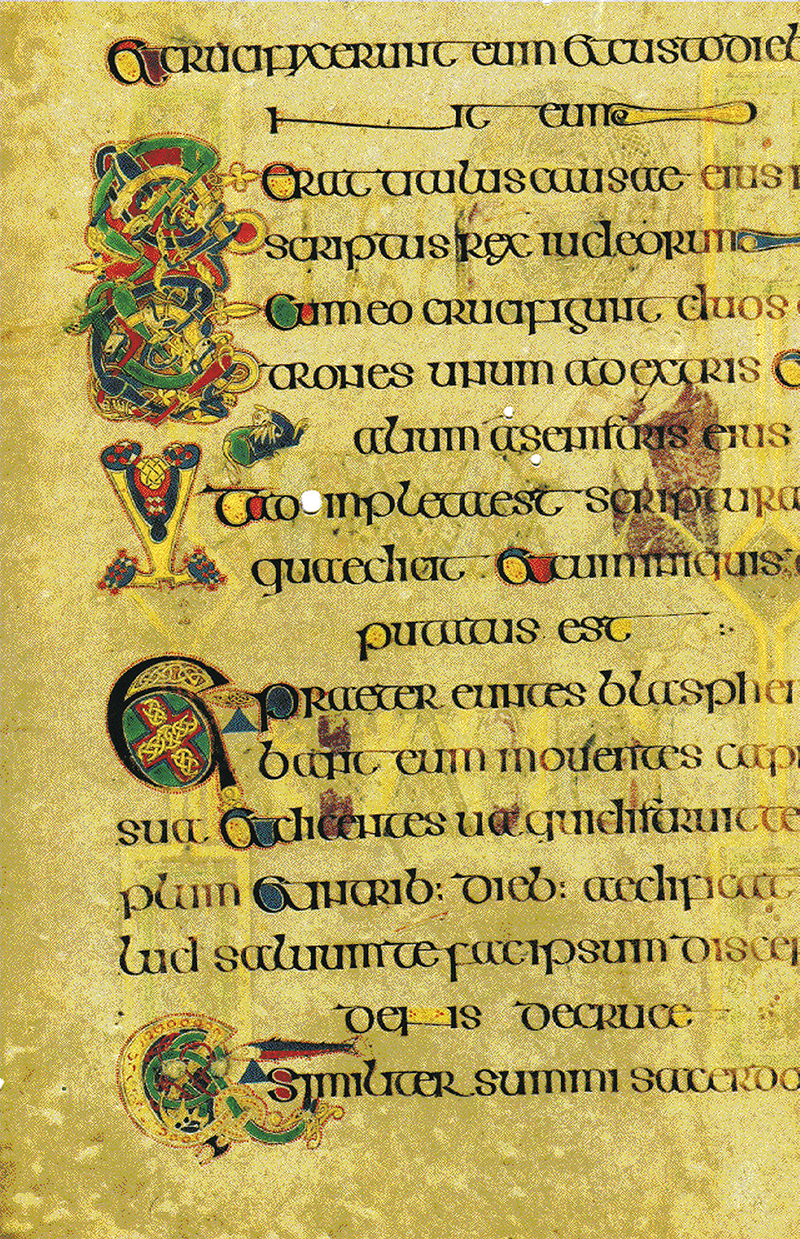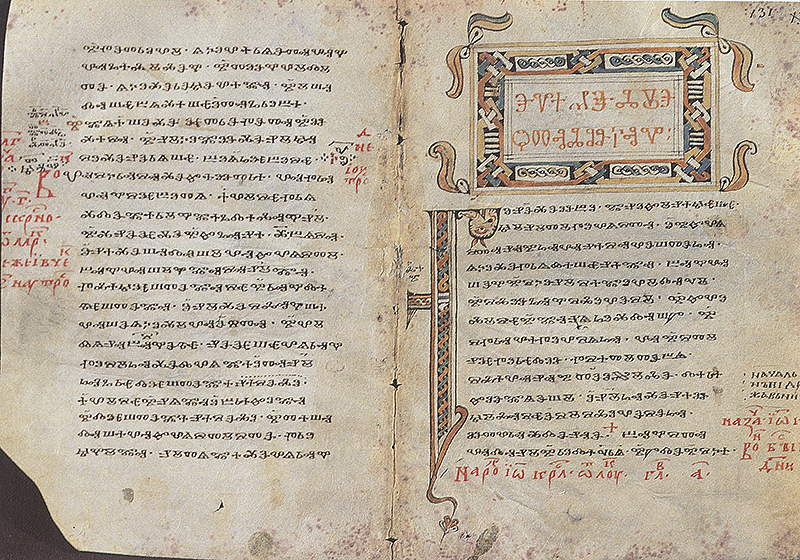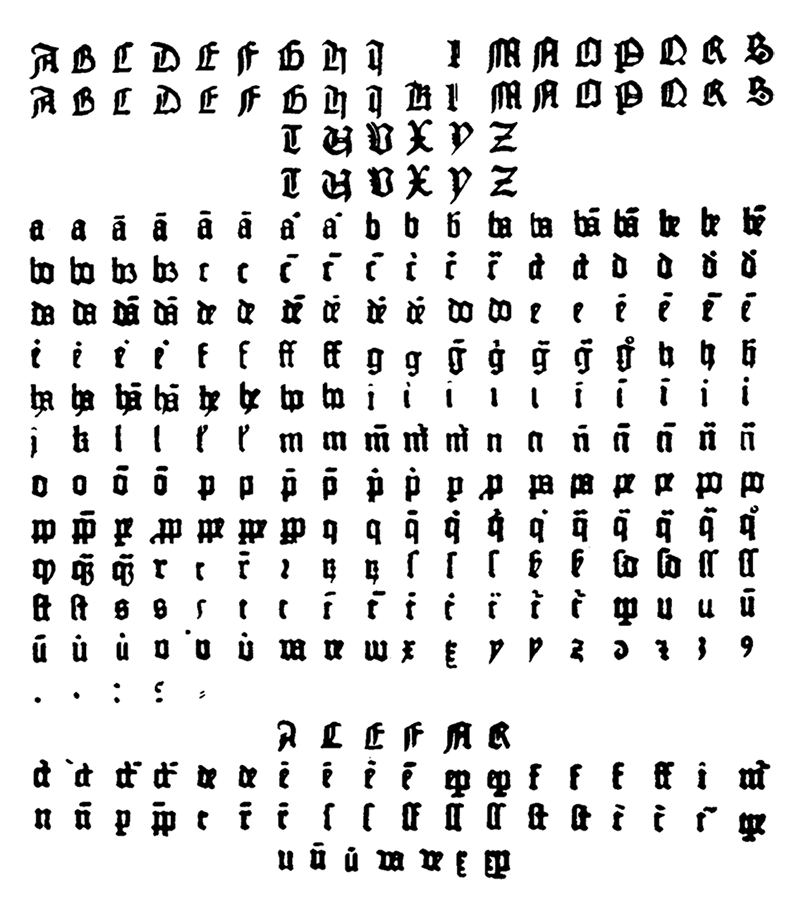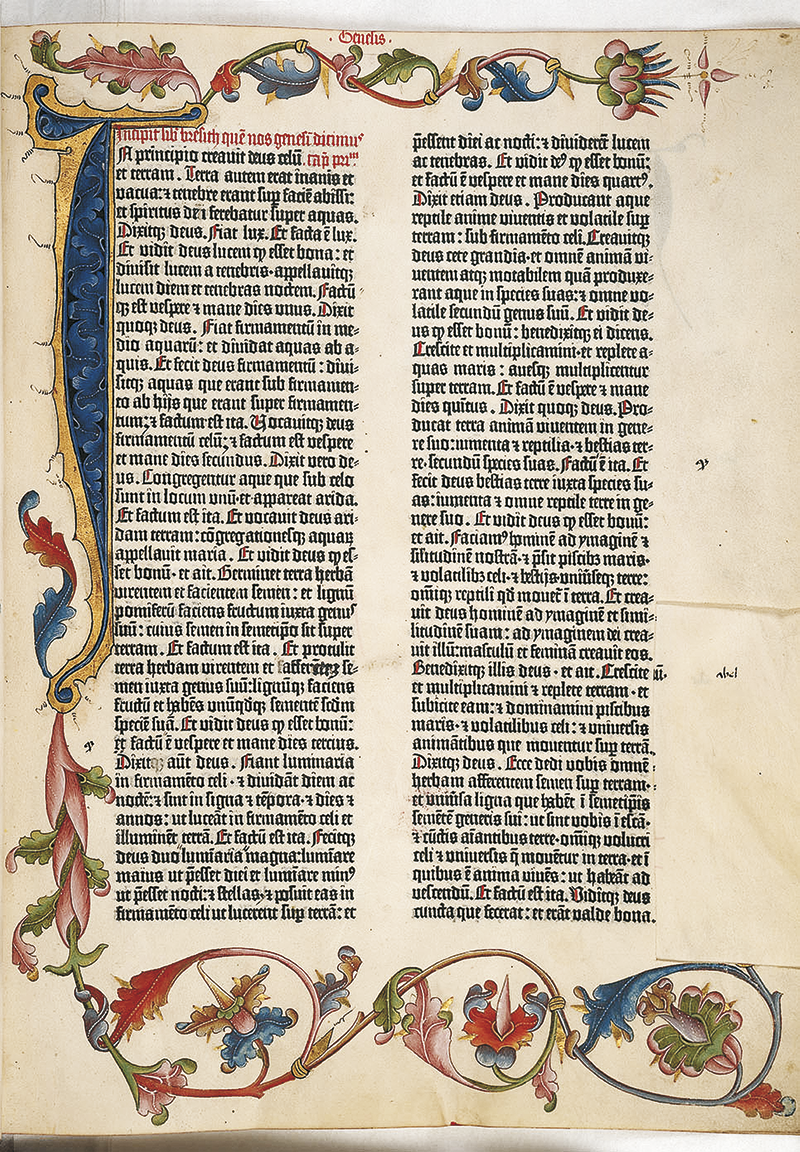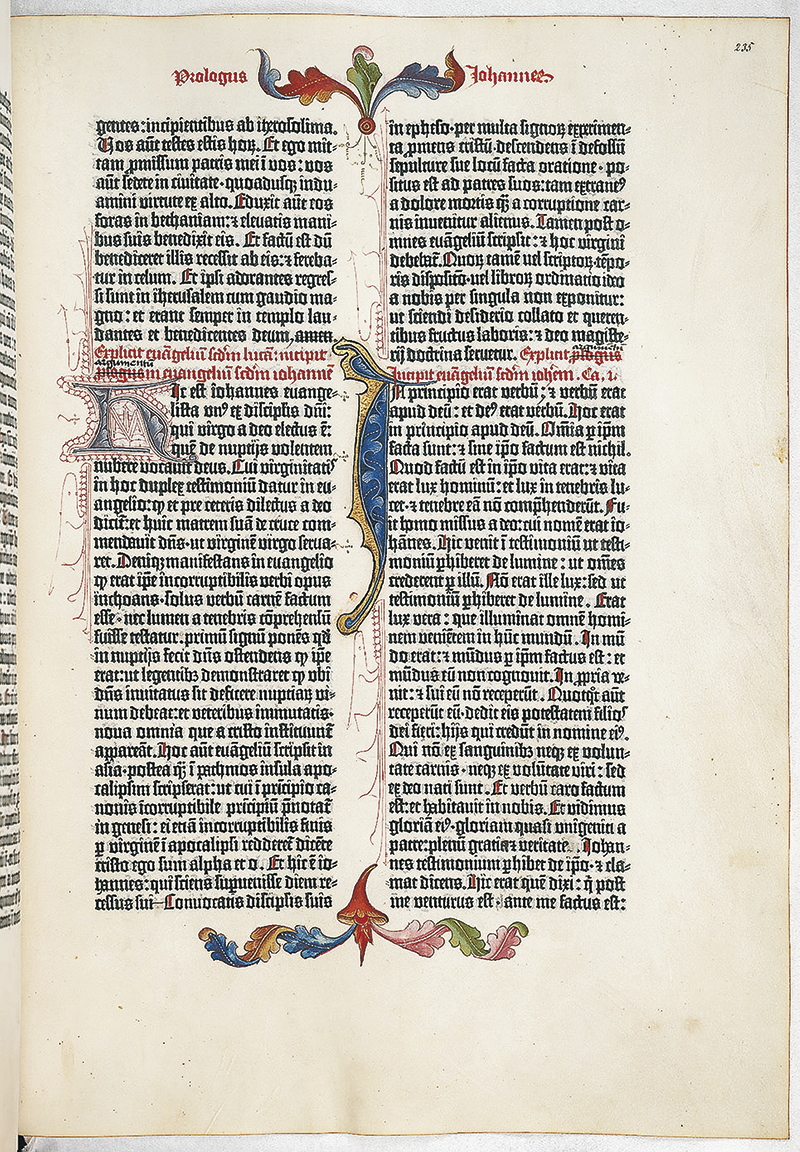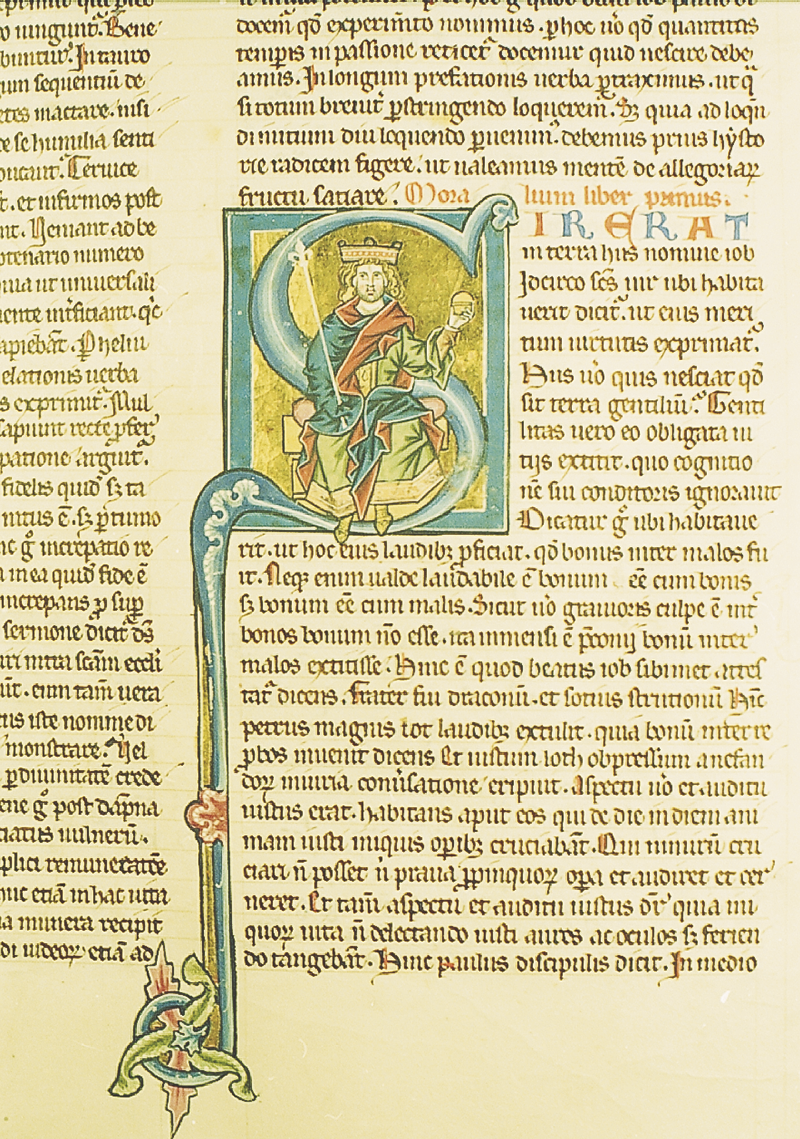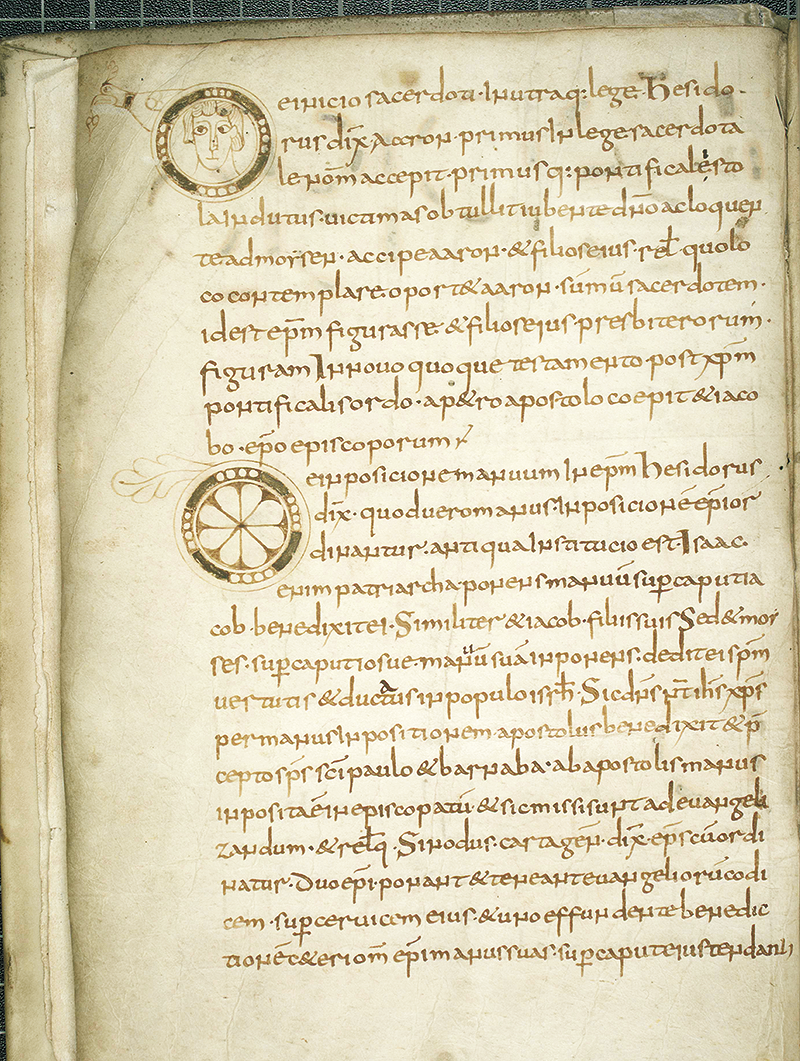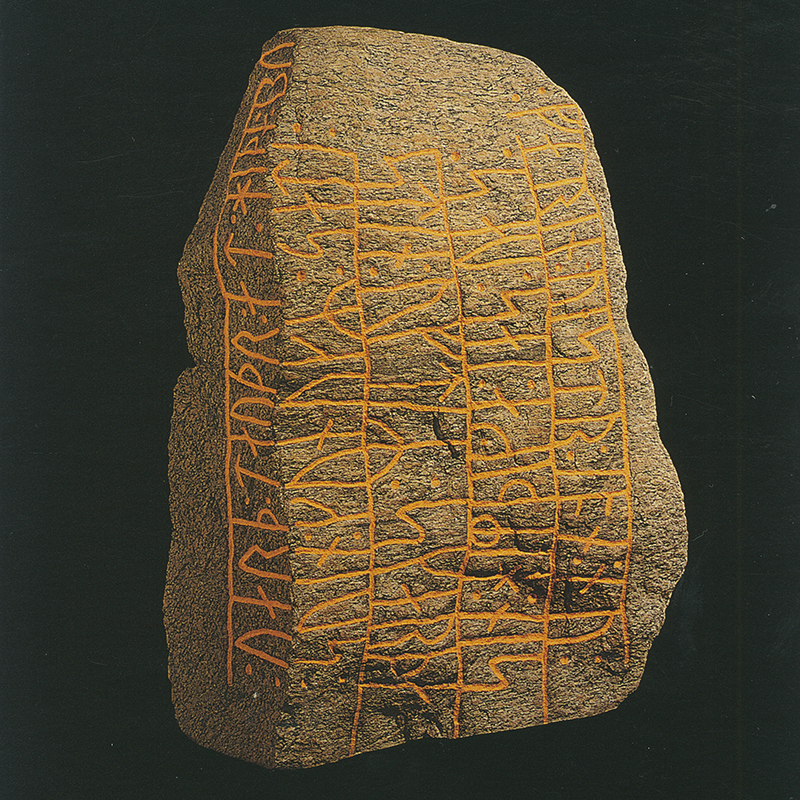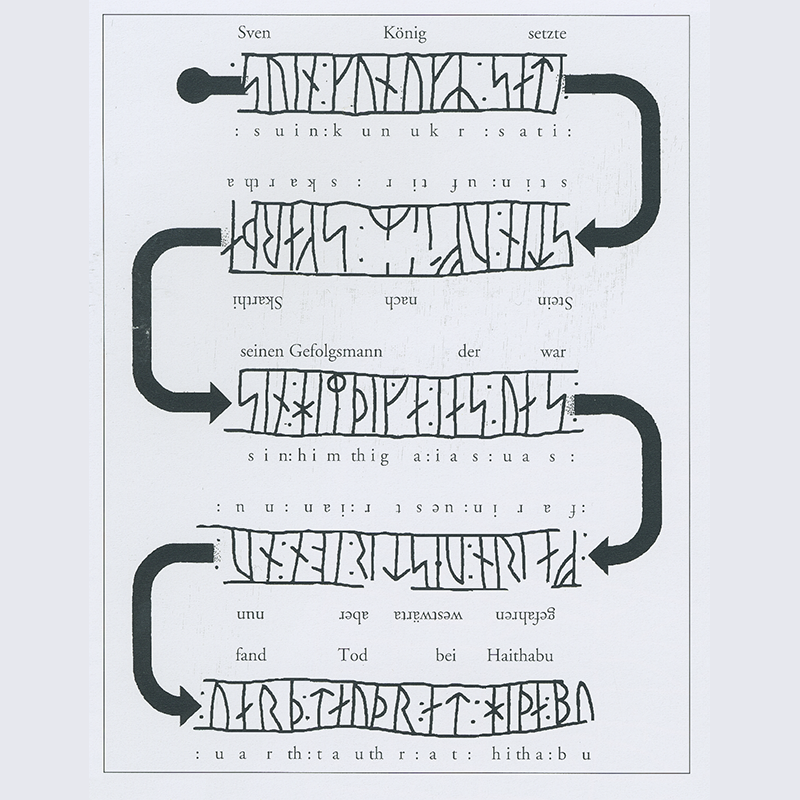
Unter Kaiser Trajan (um 117 n. Chr.) hat das Römische Imperium die Grenzen seiner Expansion erreicht. Gewiss haben die römischen Eroberungen die Errungenschaften der s. g. Zivilisation in kultureller und wirtschaftlicher Hinsicht in weiten Teilen Europas verbreitet, allerdings all zu oft auf Kosten der Freiheit der unterdrückten Völker. Ab nun gilt es, das eigene Territorium entlang der „limites“ 21 gegen die Feinde von innen und von außen zu verteidigen.
Die Völker Europas, Asiens und Afrikas befinden sich seit dem II. Jh. n. Chr. zunehmend in Bewegung. Die moderne Forschung spricht eher vom Prozess der „Ethnogenese“ (im Sinne der Bildung der Rechtsgemeinschaft um den Traditionskern des Stammes), als von der Wanderung (im Sinne der Bewegung im geografischen Sinn). Die „gens“ (lat. gens, -es = Sippe, Volksstamm, Volk) sind die Keimzellen der späteren Staaten und Völker aber auch der Sprachen und Schriften. Der mit der Reichsteilung im Jahr 395 n. Chr. eingeleitete Untergang des römischen Reiches verursachte eine Verlagerung der Machtverhältnisse in Europa. Die zunehmende Konkurrenz zwischen dem West- und Ostteil des Imperiums, sowie die Kämpfe mit den Goten, den Franken, den Vandalen, Alanen und Sueben führt schließlich zum Zusammenbruch des Weströmischen Reiches in den Jahren 476–480. 22 |
Viele der handeltreibenden Sippen haben ihre eigene Sprachdialekte und verwenden Runen als Schrift. Nach den ersten sechs Buchstaben nennt man das Runenalphabet „futhark“. Die Schreibrichtung ist bustrophedonal (wie das Beispiel des „Sharthi-Steins“ in Schleswig – Abb. links – veranschaulicht), wobei auch die s. g. ‚Wenderungen‘ und ‚Sturzrunen‘ bekannt sind. Als Quelle für die Bildung des Runenalphabets wird allgemein das lateinische Alphabet angenommen. Im angelsächsischen England, das neben Skandinavien über die meisten Funde verfügt, wird das Alphabet häufig neben dem Lateinischen auf den Gegenständen benutzt. Die Runenschrift ist auch im Einflussbereich der Franken und der Goten verbreitet. Zur Zeit der normannischen Eroberung im Jahr 1066 hat sich dennoch die lateinische Schrift durchgesetzt und die Runen beinahe vollständig verdrängt. Was die Deutung der Runen betrifft meinen einige Experten: „Wir können Runeninschriften zwar meist ‚lesen‘ – so wie wir etruskische Texte lesen können – aber ihre Bedeutung ist oft unklar, weil wir wenig über die frühgermanischen Sprachen wissen. Unter ‚Runen lesen‘ verstehen wir heute eine begründete Vermutung auf der Basis spärlicher und zweideutiger Hinweise. Ein Runenforscher meint, das erste Gesetz der Runodynamik laute: ‚Für jede Inschrift gibt es so viele Deutungen wie Gelehrte, die sich damit befassen.‘“ 23 |
Futhark Runenschrift besteht aus 24 Glyphen. 24 |
Der Untergang des römischen Reiches bewirkte eine Verlagerung der Machtverhältnisse in Europa. Viele germanisch-romanische Stämme gewinnen an Bedeutung und kämpfen um den territorialen, wirtschaftlichen, religiösen und kulturellen Einfluss: die Ostgoten in Pannonien und Italien, die Langobarden ebenfalls in Italien, die Westgoten in Spanien 25 und Frankreich, die Franken in Teilen Frankreichs und Deutschland und schließlich die Angelsachsen in England. Als eine der mächtigsten Herrscherdynastien ging aus den kriegerischen Auseinandersetzungen der nachfolgenden Jahrhunderte jene der Karolinger hervor (ab 751: Pippin der Jüngere, dann ab 768: Karl der Große). Das riesige – sich über viele Sprachgebiete erstreckende – Reich musste auch geführt, verwaltet und organisiert werden. „Die Notwendigkeit, Beschlüsse, Gesetze und Verlautbarungen für das gesamte Reich verständlich zu machen, führte zu einer gemeinsamen Schrift. Es entstand die karolingische Minuskel, die ihren formalen Ausgangspunkt in den altrömischen Schriften hatte. Es war eine aus Kleinbuchstaben bestehende Schrift, deren einzelne Buchstaben breit und rund gehalten waren.“ |
Als Sprache des karolingischen Reiches wird das am meisten gekannte und verbreitete Latein verwendet, als Verkehrsschrift dient bis in das XI. Jahrhundert die karolingische Minuskel. Diese Schrift wurde von Alkuin von York – der in Tours tätig war – im IX. Jahrhundert entwickelt. Die neugegründeten Klöster werden zu den kulturtragenden Zentren des Mittelalters und zum Ausgangspunkt der Bildungs- und Missionstätigkeit der Kirche. Eine bedeutende Schrift dieser Zeit (Ende VIII/Anfang IX. Jh.) repräsentiert das weltberühmte „Book Of Kells“, ein im Trinity College Library in Dublin aufbewahrtes Evangeliar, das um den Kanon des Eusebius von Cäsarea erweitert wurde. Dieser aus 340 Folien bestehende Prachtband wurde in der s. g. Insularen Minuskel (auch Spitzschrift genannt) geschrieben. |
Abhängig von den Anwendungsgebieten entstanden im mittelalterlichen Europa die Urkundenschrift (z. B. Merowingische Urkundenminuskel, Cancellaresca, die Scriptura elongata der Königskanzlei, die Kuriale der päpstlichen Kanzlei usw.), die Universitätsschriften (z. B. Littera bononensis, Littera parisensis, Bastarda, Textualis, Rotunda) und Humanistenschriften (Humanistica antiqua). Textualis und Cursiva sind zwei Schriftarten, die besonders für die Erstellung von liturgischen Büchern, sowie Herrschern gewidmeten Werken verwendet wurden. Sie werden allgemein in die Kategorie der gotischen Schriften eingeordnet und erreichen im XIV/XV. Jahrhundert ihre Blütezeit.
Für Europa ist die älteste Schrift der Slawen, das glagolitische Alphabet, erwähnenswert. Sie wurde von dem griechischen Missionar Konstantinos (später Kyrillos genannt) um 860 geschaffen. Diese Schrift behauptet sich bis heute in dem Einzugsgebiet der griechisch-orthodoxen Kirche (Russland, Serbien, Teile Kroatiens, Bulgarien). Das griechische Alphabet kann man nicht als Inspirationsquelle für die kyrillische Schrift bezeichnen. Kyrillisch ist eine Originalschrift, die eine Abzweigung der griechischen Majuskelschrift des IX. Jahrhunderts darstellt. 27 |
Für die Entwicklung der Schrift ist die Erfindung des Buchdrucks durch Henne Gensfleisch (besser bekannt als Johannes Gutenberg, 1400–1468), der nach seinen Strassburger Jahren (1434–1444) ab 1448 wieder in Mainz arbeitet, von epochaler Bedeutung. Zwischen 1452–1455 druckt er seine 42-zeilige (lateinische) Bibel: „Gedruckt wurde schon vor Gutenberg per Holzdruck. Hierbei wurde Papier auf den bearbeiteten und mit Farbe versehenen Holzstock gelegt und abgerieben – ein aufwendiges und langwieriges Verfahren. Grundgedanke der Erfindung Gutenbergs war die Zerlegung des Textes in alle Einzelelemente wie Klein- und Großbuchstaben, Satzzeichen, Ligaturen und Abkürzungen, wie sie aus der Tradition der mittelalterlichen Schreiber allgemein üblich waren. Diese Einzelelemente wurden als seitenverkehrte Lettern in beliebiger Anzahl gegossen, schließlich zu Wörtern, Zeilen und Seiten zusammengefügt. Urform oder Prototyp für jeden Buchstaben war der Stempel. In die Stirnseite eines Stahlstifts wurde das Zeichen geschnitten, so dass sich ein seitenverkehrtes präzises Relief ergab. Nun wurde der jeweilige Stempel, die Patrize, in einen rechteckigen Block aus weicherem Metall, in der Regel wohl Kupfer, ‚abgeschlagen‘, d. h. senkrecht mit dem Schlag eines Hammers eingetieft. Die so erzeugte Matrize musste nachbearbeitet und begradigt werden, so dass ein rechtwinkliger Kubus mit geraden Seiten entstand. Das seitenrichtige Bild sollte eine einheitliche Tiefe haben, weshalb die Oberfläche mit einer Feile bearbeitet wurde. Um den Guss einer Letter zu bewerkstelligen, entwickelte Gutenberg das Handgießinstrument. Zwei Teile umschließen einen rechteckigen Gießkanal, dessen eines Ende durch Einsetzen der Matrize verschlossen wurde. Nach dem Guss der Lettern im Handgießinstrument musste der Angusszapfen entfernt werden.“ 28 |
Die neue Technologie, die einerseits erstmalig hohe Auflagen von schriftlichen Werken ermöglichte, andererseits auch propagandistischen Zielen diente, legte den Grundstein für die rasche Verbreitung des Geistes der Reformation und der Aufklärung. Die gutenbergsche Drucktechnik wurde in den folgenden 350 Jahren nicht wesentlich verändert.
Ab nun ist jeder Herrscher, Adelige bzw. Wohlhabende in der Lage, sein Gedankengut in schriftlicher Form der Welt zu unterbreiten. |
21 lat. limes, limites = Grenzwall, Schneise.
22 Das Byzantinische Reich übersteht diese Phase weitgehend unbeschadet – knapp 1000 Jahre später am 29. Mai 1453 mit dem Tod des Kaisers Konstantin des XI. endet die 2000-jährige Geschichte des Römischen Reiches.
23 „So liest man Runen“, in: Robinson A., Die Geschichte der Schrift, Albatros Verlag, Düsseldorf: 2004, S. 178.
24 Abbildung nach: „So liest man Runen“, in: Robinson A., Die Geschichte der Schrift, Albatros Verlag, Düsseldorf: 2004, S. 178.
25 Das Tolosanische Reich hat in weiterer Folge während der Reconquista in Spanien identitätsstiftende Funktion.